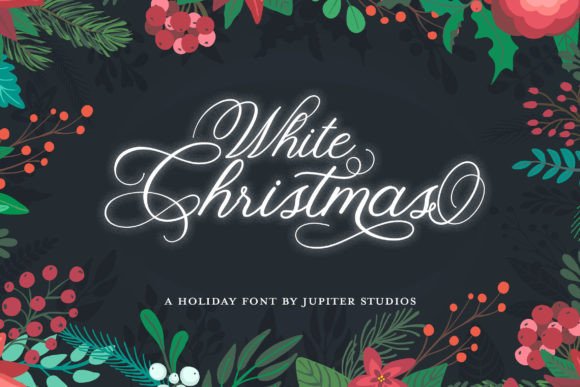
White Christmas
Việc tìm kiếm các thành phần thiết kế phù hợp có thể là một thách thức, nhưng White Christmas cung cấp một bộ sưu tập đặc biệt giúp nâng tầm công việc của bạn ngay lập tức.
Được chế tác với độ chính xác cao, White Christmas cung cấp các vector sạch, kiểu chữ mượt mà và giấy phép thương mại để bạn yên tâm.
Cho dù bạn đang tạo sản phẩm POD (In theo yêu cầu), thiệp mời đám cưới hay đồ họa mạng xã hội, White Christmas đều là một sự lựa chọn lý tưởng.